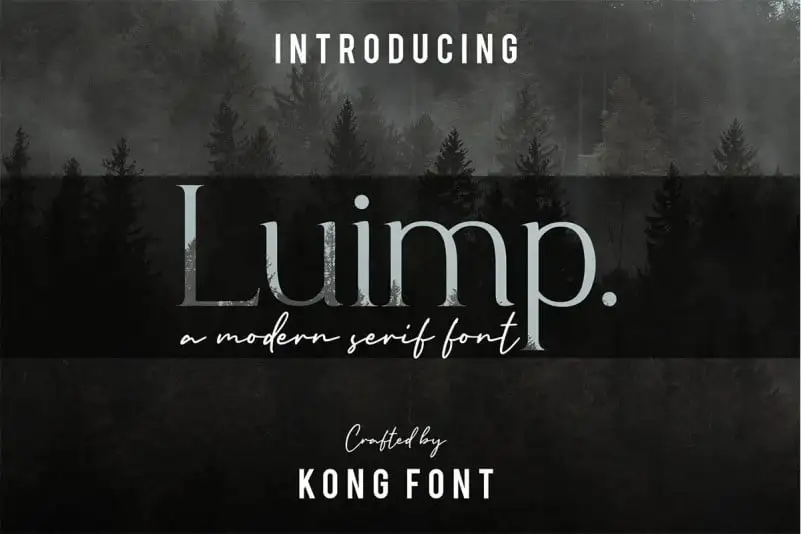
A Luimp Serif Font é uma tipografia com estilo moderno de sans serif que incorpora uma aparência limpa e elegante. Este tipo de letra foi criada pelo fontkong, um lugar onde designers compartilham suas criações únicas. A Luimp oferece uma sensação de personalização imediata aos designs de logotipos, marca, design editorial, convites para casamentos e embalagens, ou qualquer trabalho gráfico original que você possa criar. Com seu charme tipográfico cuidadosamente produzido à mão, a Luimp adicionará um toque único e sofisticado a seus projetos de arte. É perfeita para dar um toque especial aos elementos visuais de sua identidade visual ou qualquer outro projeto gráfico que desejar dar uma cara diferenciada.